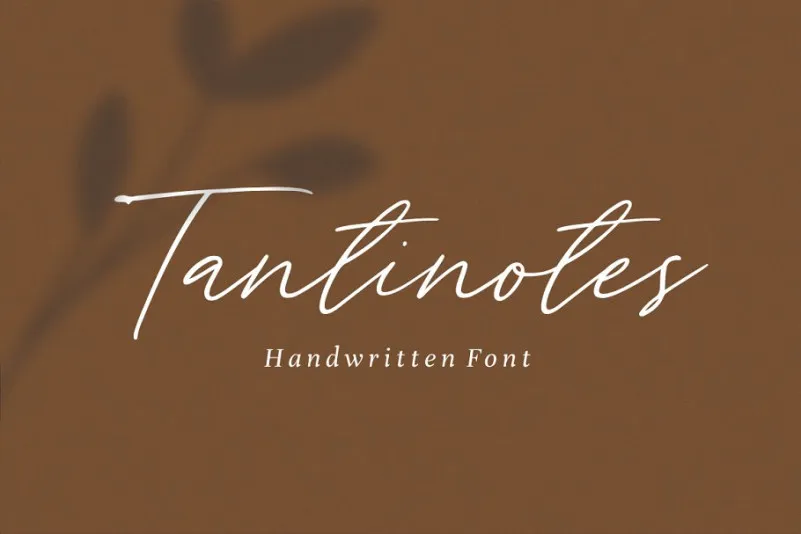
Tantinotes Handwritten Font – Download Grátis
Descubra agora a Tantinotes Handwritten Font, uma fonte escrita à mão natural projetada pela 178-MC. Esta é uma font premium que está disponível para download gratuito nesta plataforma hoje, oferecendo um gráfico elegante e realista ideal para várias aplicações. Com seu estilo de escrita autêntico, a Tantinotes Handwritten Font é perfeita tanto para design de logomarca quanto para criação de convites, identidade visual, embalagens, fotografias e até mesmo para anúncios em redes sociais. Esta font será uma adição valiosa ao seu portfólio de recursos gráficos, permitindo-lhe criar designs atraentes com um toque autêntico de escrita à mão. Não deixe de experimentar e descobrir como esta font pode transformar suas criações.